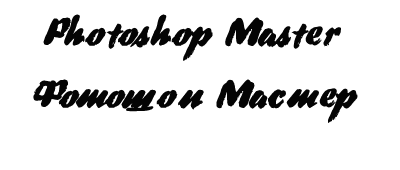
цифры не работают!!
восклицательный знак не работает и буква ё
норм такой
Шрифт хороший, только на счет вопросительного и восклицательного знака что то не хочет. Может это только у меня?
Шрифт больно знакомый... Пахнет советскими временами... А так - отличный!